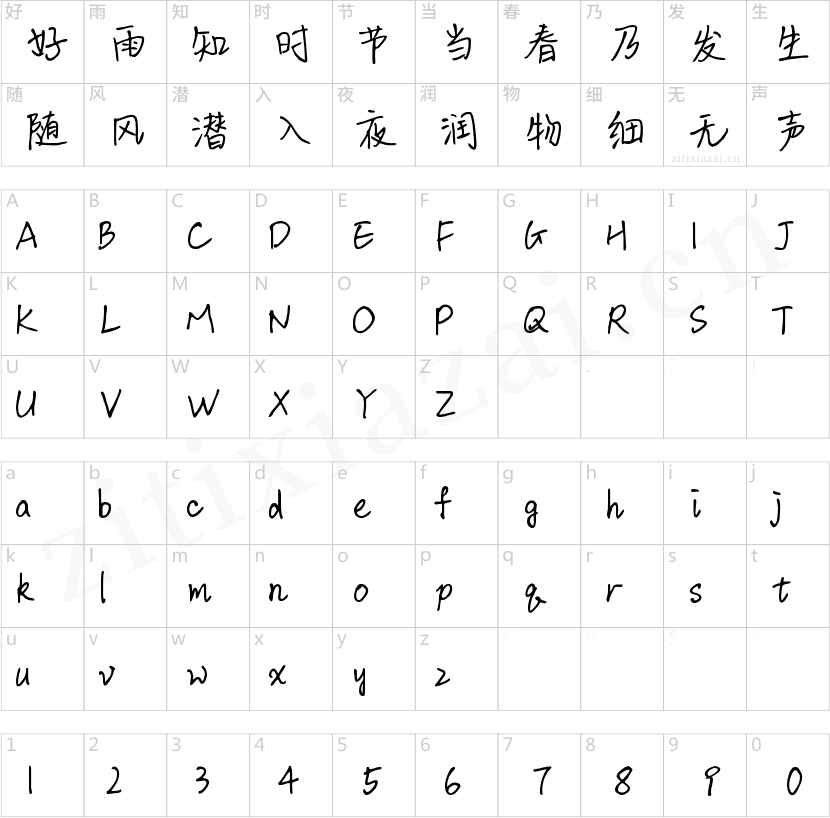
Aa夏有森光
Aa夏有森光字体
Aa夏有森光是一款非常具有艺术性的字体,它的设计灵感来源于对古典艺术的研究,同时又融入了现代字体设计的元素。字形优美,笔画粗细变化自然,给人以大气、典雅的感觉。Aa夏有森光是一款既传统又现代的字体,它的设计充满艺术感,美观大方,实用性也非常强。无论是对于设计师还是对于普通读者来说,都是一种非常不错的字体选择。Aa夏有森光适合用于具有艺术感的场合,比如海报、宣传单张、书籍封面等。由于其字形流畅且具有动态感,也适合用于大量的文本排版,如报纸、杂志等。